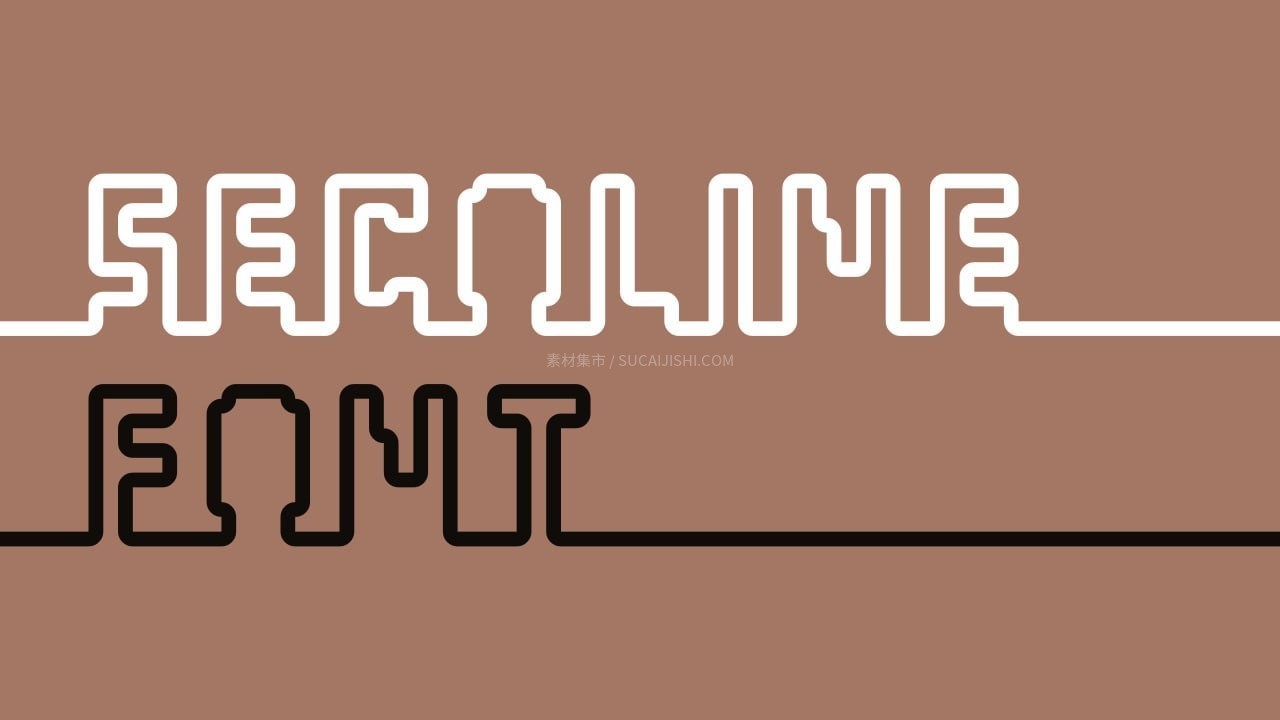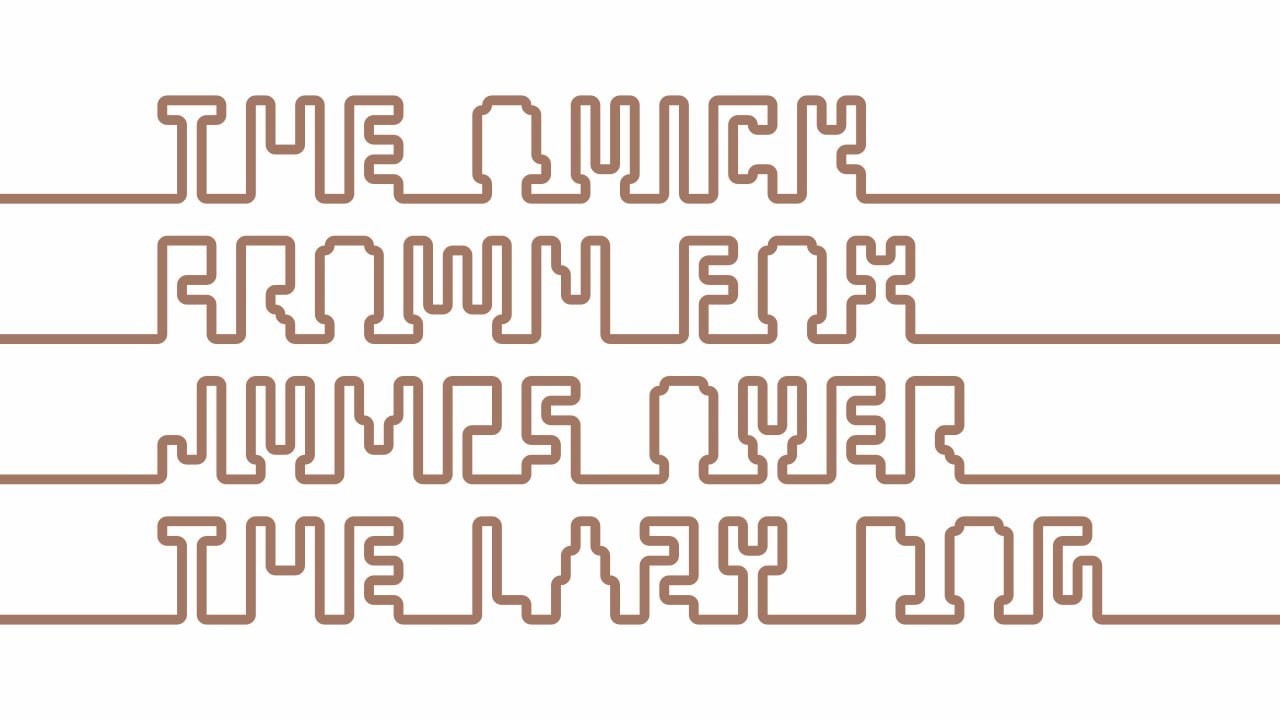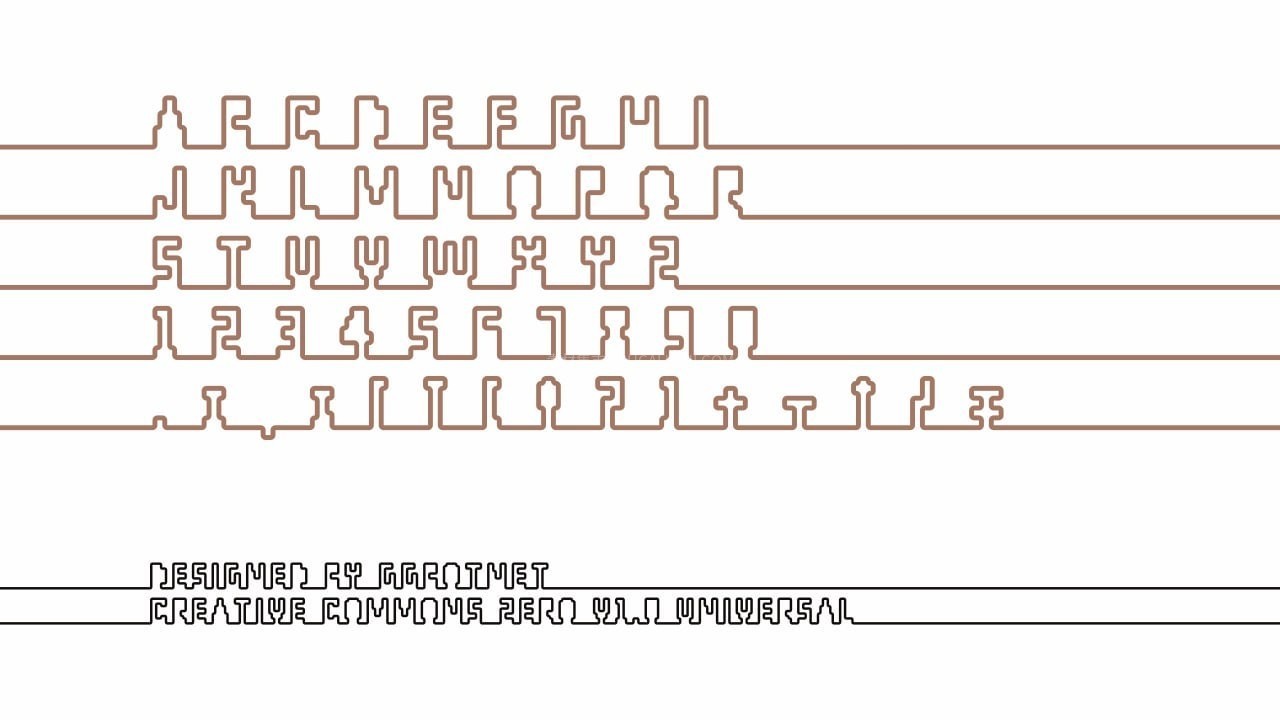
Secoline极简单线英文字体,免费可商用
Secoline 是一款基于 CC0 1.0协议 发布的顶级开源字体。其设计灵感源自不间断的连续曲线(Continuous Line),通过极简的单线结构勾勒出充满现代感与科技气息的字形。由于其处于公有领域(Public Domain),你可以无限制地将其用于任何商业项目、修改甚至重新发布,是追求设计自由与版权安全的极致之选。